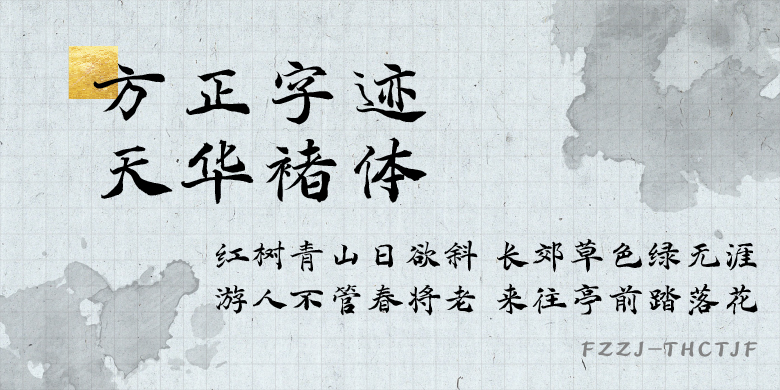
方正字迹-天华褚体
方正字迹-天华褚体,这款字体结构工整、笔画清晰,兼顾美观与易读性,适用于标题、正文、海报、包装、LOGO 等多种场景。字形优雅稳定,风格百搭耐看,适配日常排版与创意设计,让文字呈现更舒适、更具质感。方正字迹-天华褚体一笔一画,皆是细节,以均衡的比例、流畅的线条打造舒适视觉体验,字形端正大气,风格简约现代。无论是商业设计、品牌宣传还是日常排版,都能轻松驾驭,让文字更有格调与力量。方正字迹-天华褚体字体下载。
字体品牌: 方正字迹 设计师:温天华 字体分类:楷书 字体属性:精品字 字符集:大陆简体(GB2312-80)、简繁扩展(GBK) 发布时间: 2022
方正字迹-天华褚体,用笔丰富,有方有圆,在藏有露,一波三折,点画轻重极尽变化,欹侧俯仰而是不失重心,中宫饱满,茂密丰满。其笔力坚实,动势强劲,气脉通畅,憨厚不失妩媚,飘逸仍见端庄。结构牵丝暗连,速度极快,俯仰呼应,各有所据,气息盈满,妙笔生花。
该字体由中国硬笔书法家协会会员,网络书法教学名家温天华书写。既具备褚遂良的《大字阴符经》和《雁塔圣教序》的笔法,又有赵松雪的笔意。9664字的字库,里面简体和繁体并存。
一般适用于标题,人物对话,台词等。这款字体的笔划,加强了笔划的粗细变化,使得它可以轻松驾驭大标题的展示。适用于文化类的宣传设计,以及商业类品牌的广告和商品包装设计。